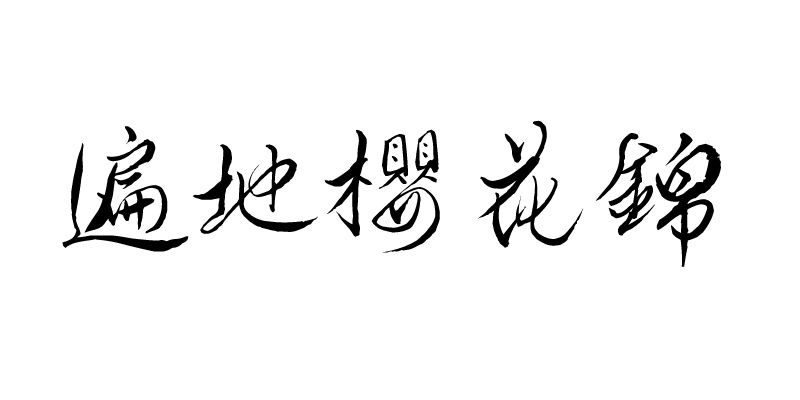
Questa serie di font contiene caratteri tipografici giapponesi originali scritti a mano e basati sulla calligrafia a penna lanciati nel 2002. Con il loro aspetto caloroso, questi caratteri attireranno l’attenzione del lettore sui punti chiave di un design.